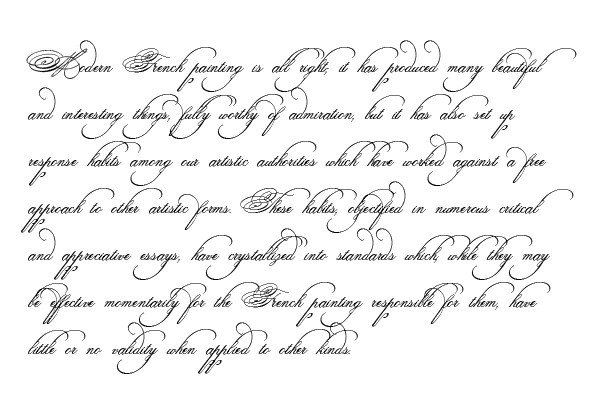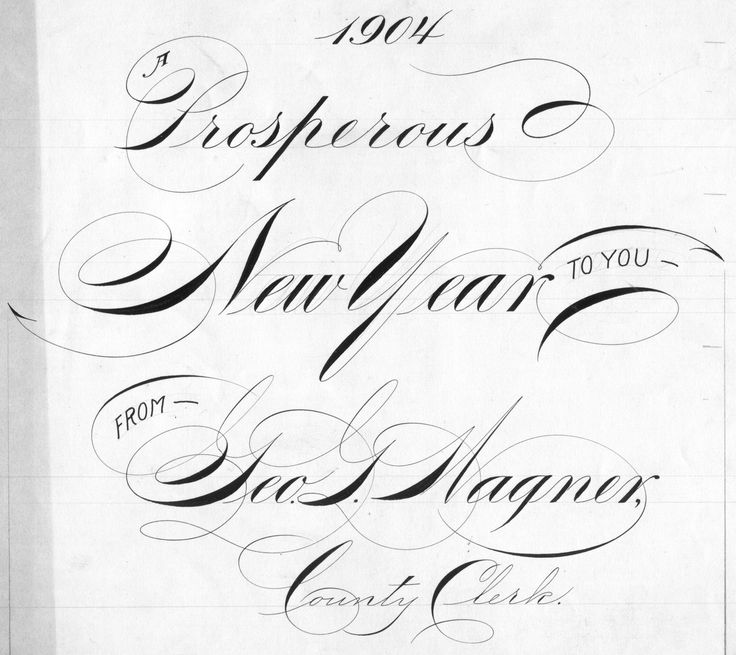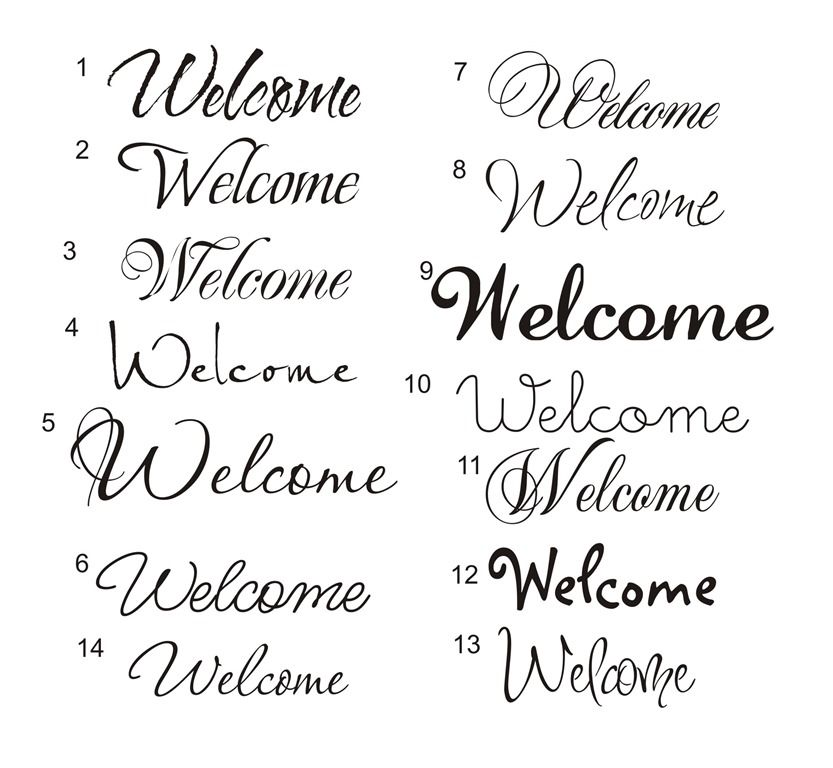
Немного о шрифтах на сайте — Дизайн на vc.ru
Одним из способов коммуникации с пользователем является типографика. Хороший шрифт на сайте создает настроение, акцентирует внимание человека на важных элементах, его легко читать и он также является отдельным элементом дизайна! Как же правильно выбрать подходящий шрифт?
В первую очередь необходимо определиться с концепцией проекта, какую цель вы преследуете, какое настроение вы бы хотели донести до пользователя? Здесь стоит обратить внимание на несколько факторов:
- Какой на сайте будет контент — какие тексты будут присутствовать на сайте, о чем они будут. Например, обучающие материалы по финансовой грамотности и реклама новой детской игрушки несут абсолютно разное настроение, соответственно и шрифт будет разный.
- Дизайн сайта — шрифт должен подчеркивать дизайн, дополнять его и не противоречить основной идее.
- Целевая аудитория — для каждого типа аудитории подходит определенный шрифт, который также отражает настроение и соответствует концепции всего сайта.
- Восприятие пользователем — длинные тексты к которым применен нечитаемый, но очень красивый шрифт никакой пользы не принесут, а только наоборот, пользователь просто покинет такой сайт и будет искать необходимую ему информацию на других ресурсах.
После определения концепции, цели и аудитории у нас уже есть примерное понимание того, какой шрифт нам может подойти. А из чего выбирать? В наше время существуют уже тысячи разных шрифтов, но основные их классификации все таки можно обозначить:
- Антиква — шрифты с засечками. Раньше считалось, что такие шрифты больше подходят для печатных изданий, так как засечки помогают формировать строку, но сейчас они часто используются и для онлайна. Классические, элегантные шрифты.
- Гротеск — шрифт без засечек. Гротеск привычнее для онлайн-пользователя, он часто используется на сайтах, в социальных сетях и на самих устройствах. Когда шрифт этого класса только появился, он использовался для привлечения внимания в рекламе и в заголовках.
Минимализм, динамичность.
- Рукописные шрифты — исходя из названия можно понять, что это шрифты, которые имитируют рукописный текст.
- Акцидентные (декоративные) — особенность этой категории в том, что такие шрифты также не подходят для набора основного текста, а используются лишь для акцентирования и привлечения внимания.
Как правило, первые две категории шрифтов можно использовать для всего, как для длинных текстов, так и для заголовков, и для создания акцентов. Главное правильно подобрать размер, сочетание шрифтов между собой и другие параметры. А вот рукописные и акцидентные шрифты лучше использовать только для акцентов в дизайне сайта, так как их сложнее воспринимать.
Постепенно мы подобрались к вопросу сочетания шрифтов между собой. Как лучше сочетать шрифты? Ниже несколько советов:
- Одно из основных правил о котором говорится повсеместно — максимум три шрифта на одном сайте, не больше.
При этом каждый из выбранных шрифтов должен использоваться только в своей зоне ответственности — заголовки, основной текст, акценты. Шрифты, так же как логотип и цвета могут стать якорем компании и клиенты будут ассоциировать вас с определенными шрифтами, поэтому лучше использовать небольшое количество шрифтов, а также гармоничное сочетание шрифтов украшает визуальную картину сайта и помогает выстроить смысловую иерархию. - Каждый шрифт несет определенное настроение и это настроение должно быть единым у сочетаемых шрифтов. Если выбор пал на строгий, серьезный шрифт, то и остальные шрифты на сайте должны отражать тоже самое настроение. Сочетать между собой элегантный, строгий шрифт с динамичным, легким шрифтом все таки не стоит.
- Шрифты с засечками и без засечек прекрасно сочетаются. Как мы писали выше, гротеск изначально использовался для заголовков или рекламы, а вот антиква для основного текста. Такие шрифты идеально друг друга дополняют.
- Не забывайте, что у шрифтов можно менять размер, наклон и другие параметры для того, чтобы как-то разнообразить текст.
- Заголовок всегда должен отличаться. Как в примере с антиквой и гротеском, другой шрифт привлекает внимание и, опять же, создает необходимую смысловую иерархию.
Осталось поговорить о технических характеристиках шрифтов, а конкретно о размере. Какой размер станет оптимальным и какое должно быть соотношение между заголовками и основным текстом? Размер основного текста на сайте не должен быть меньше 12px, длина строки не должна превышать 600px. Это основные рекомендации, которые подойдут в любой ситуации, остальное — дело индивидуальное. Сайты бывают разные, где-то намерено используются очень большие размеры для заголовков, так как это часть дизайна, а какие-то сайты оформлены в стиле новостной ленты и там применяются стандартные размеры для заголовков, основного текста и каких-либо подписей.
Где искать шрифты и полезную информацию по работе с ними?